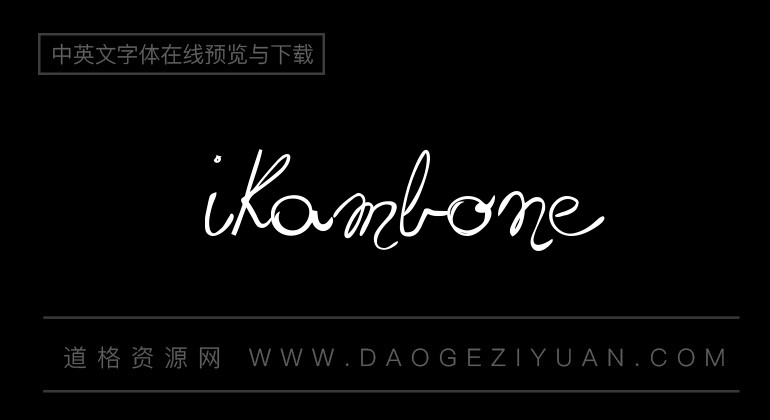
Bikambone 是一款由南非设计师 Thabisa Mjo 创作的字体,它的特点是具有传统非洲风格的复古字体。Bikambone 字体以“Bikambone”这个名字取自南非语言,意思是“我们之间”。它有着浓郁的非洲气息,既可以用于商业广告、标志和标题,也可以用于海报、社交媒体和手写文字。Bikambone 字体有着独特的复古风格,它的大小、宽度和行高都可以调节,可以让你轻松创作出与众不同的设计作品。内容介绍
Bikambone是一款非常不错的手写艺术字体,具有很好的视觉感,适合于文化类的宣传设计、商业类品牌的广告和产品包装设计以及个性化文字排版等较多场景。